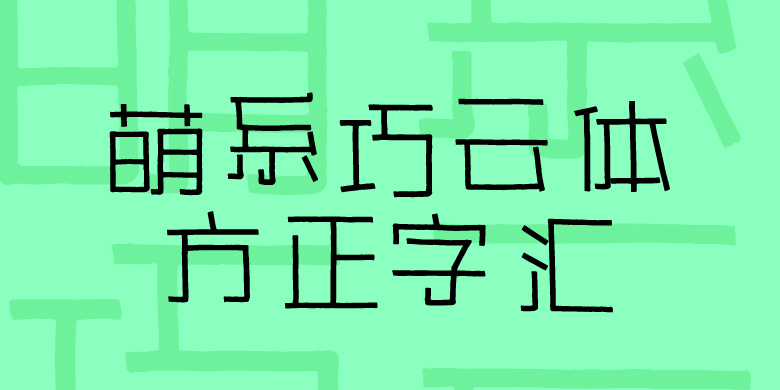
方正字汇-萌系巧云体
方正字汇-萌系巧云体,这款字体结构工整、笔画清晰,兼顾美观与易读性,适用于标题、正文、海报、包装、LOGO 等多种场景。字形优雅稳定,风格百搭耐看,适配日常排版与创意设计,让文字呈现更舒适、更具质感。方正字汇-萌系巧云体一笔一画,皆是细节,以均衡的比例、流畅的线条打造舒适视觉体验,字形端正大气,风格简约现代。无论是商业设计、品牌宣传还是日常排版,都能轻松驾驭,让文字更有格调与力量。方正字汇-萌系巧云体字体下载。
萌系字体的第三种,想着妈妈写的。字体设计中既有传统汉字方方正正的规矩,又有无限包容的创意,还有一些或多或少的笔画调皮,像极了妈妈传达给我的骨子里传统的规矩、包容与宠爱。